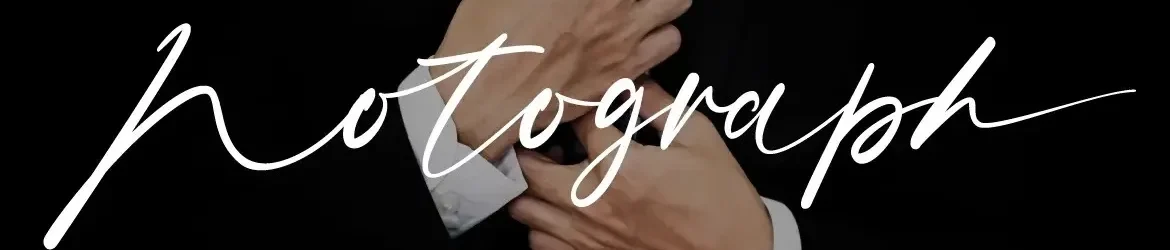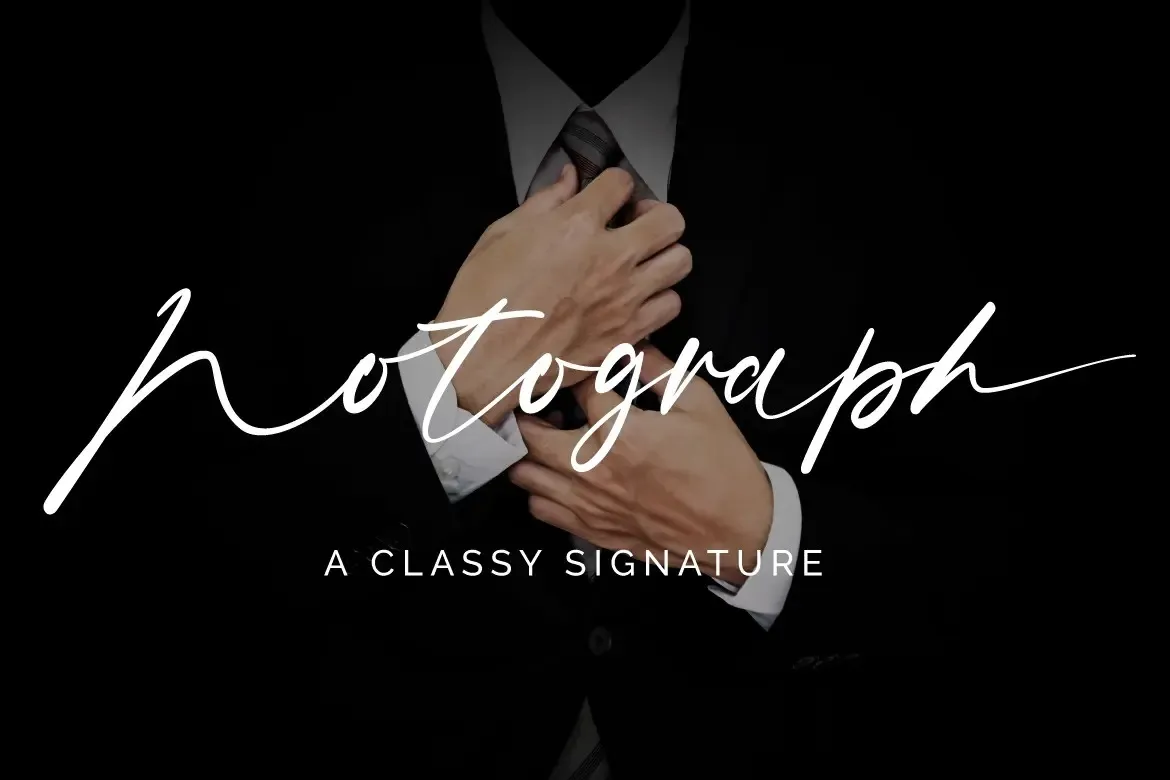
Notograph Font – Fonte Grátis
Notograph Font
Esta é uma fonte script casual chamada Notograph que foi criada pelo Studio FallenGraphic. Com traços finos e personagens curiosos e divertidos, ela oferece uma experiência única de escrita. Além disso, a fonte inclui PUA encodadas, permitindo que você acessasse facilmente todos os caracteres adoráveis ​​e swashes presentes. Esta font também vem com um grande número de recursos especiais como alternativas de gíria e ligaturas, tornando-a perfeitamente adequada para um amplo espectro de projetos, desde logotipos até citações. Estou pronto para explorar a personalidade leve dessa fonte? Espero que você goste de Notograph! Parabéns por visitar e baixar nossa fonte.